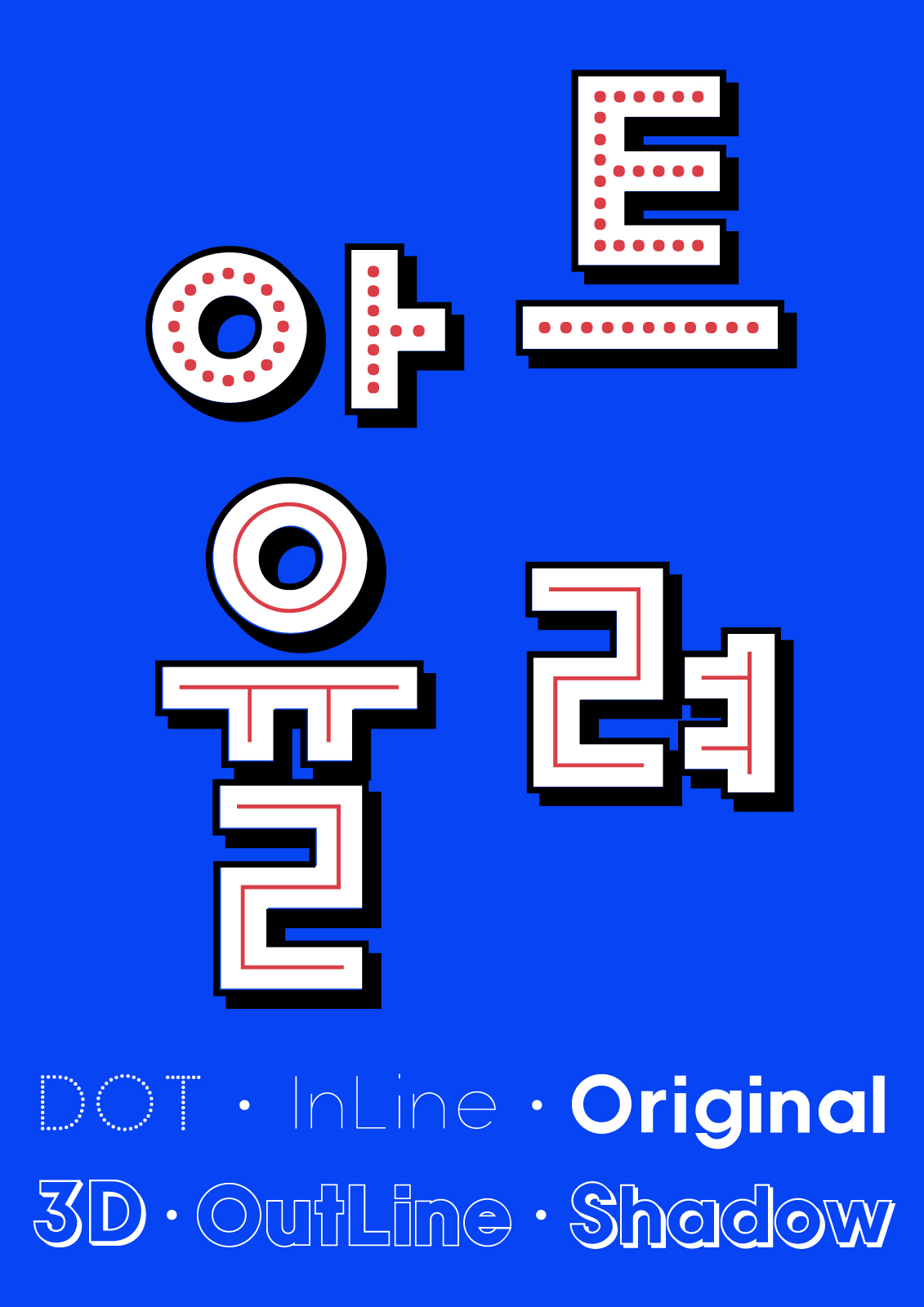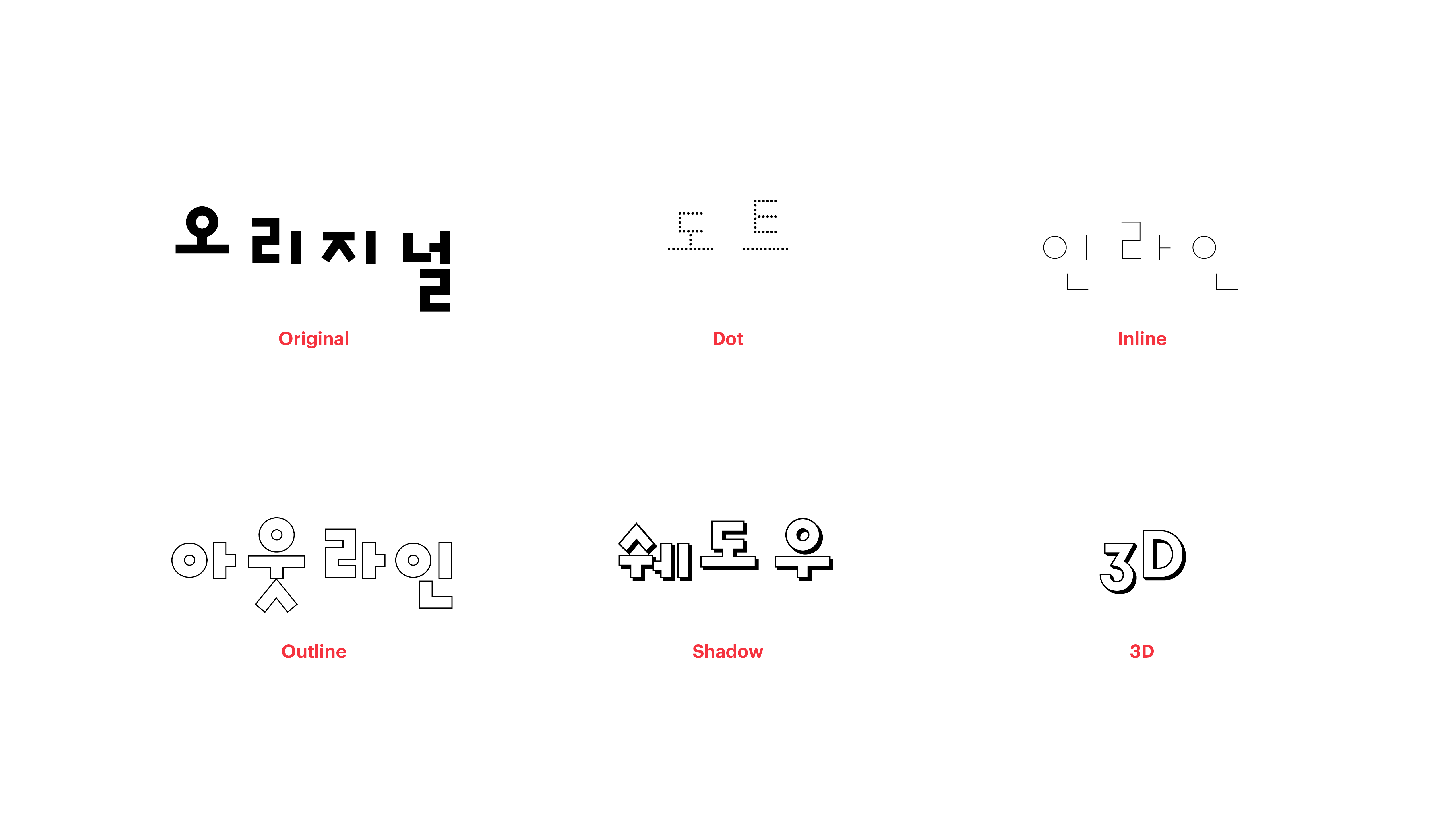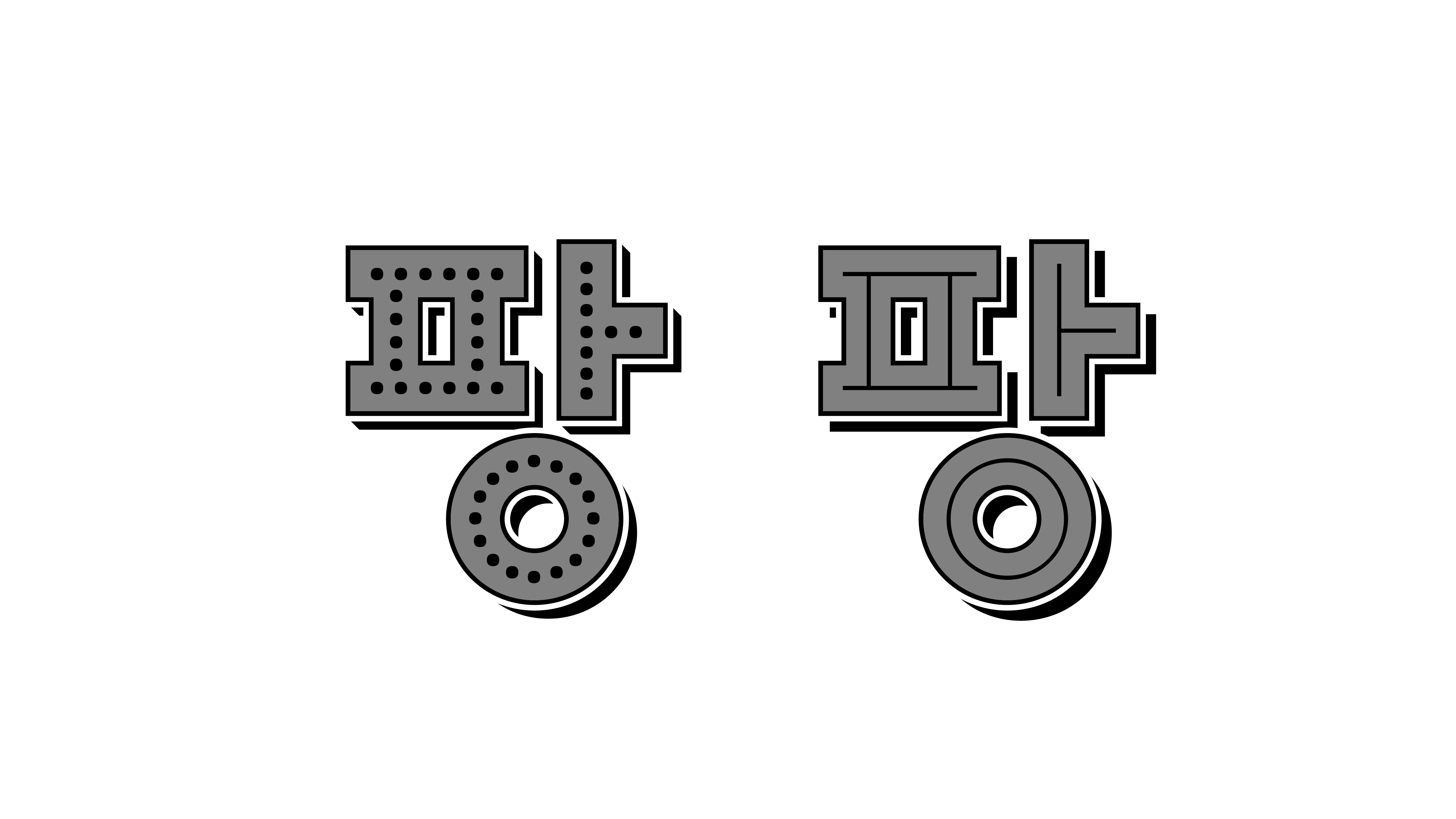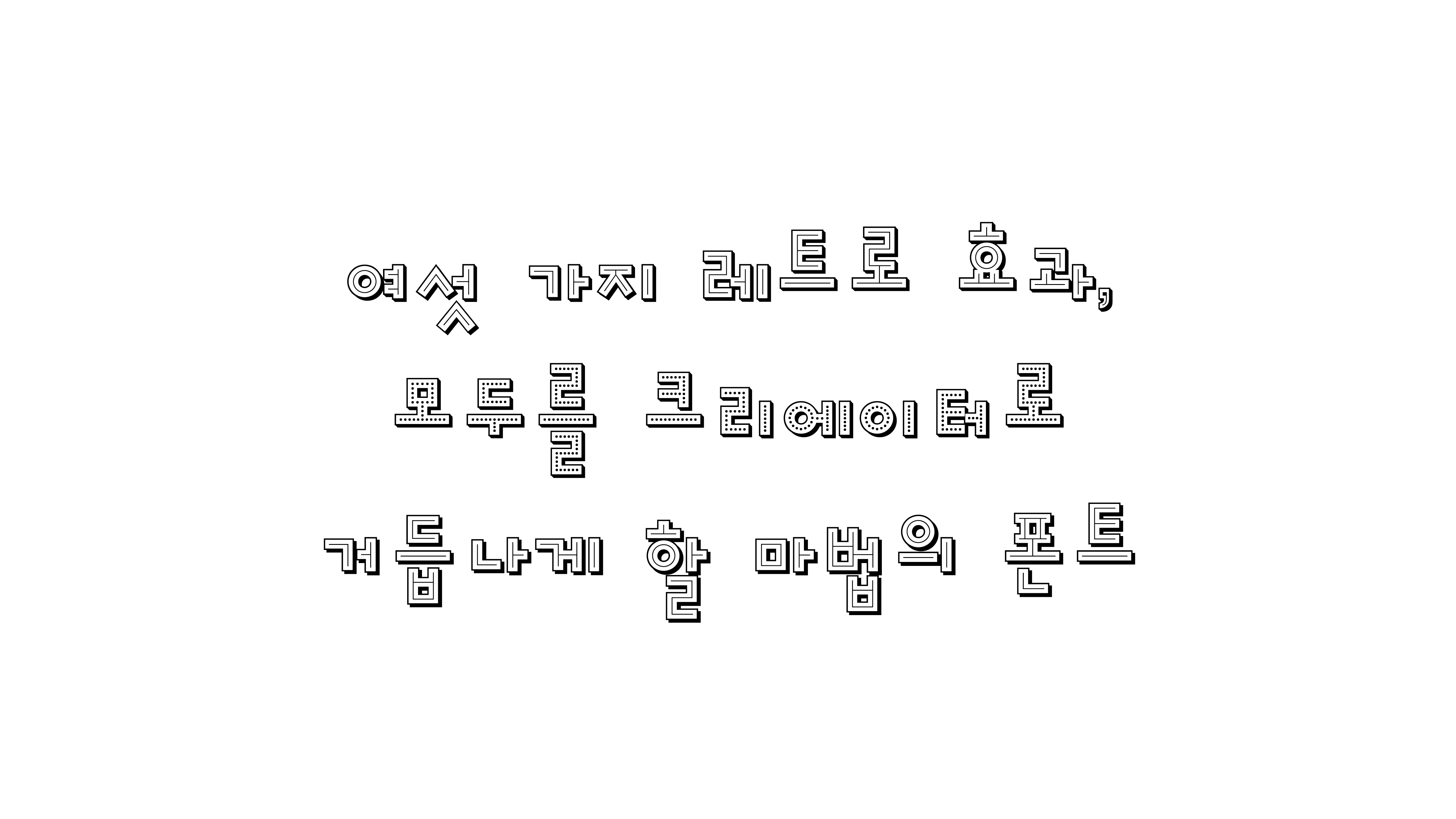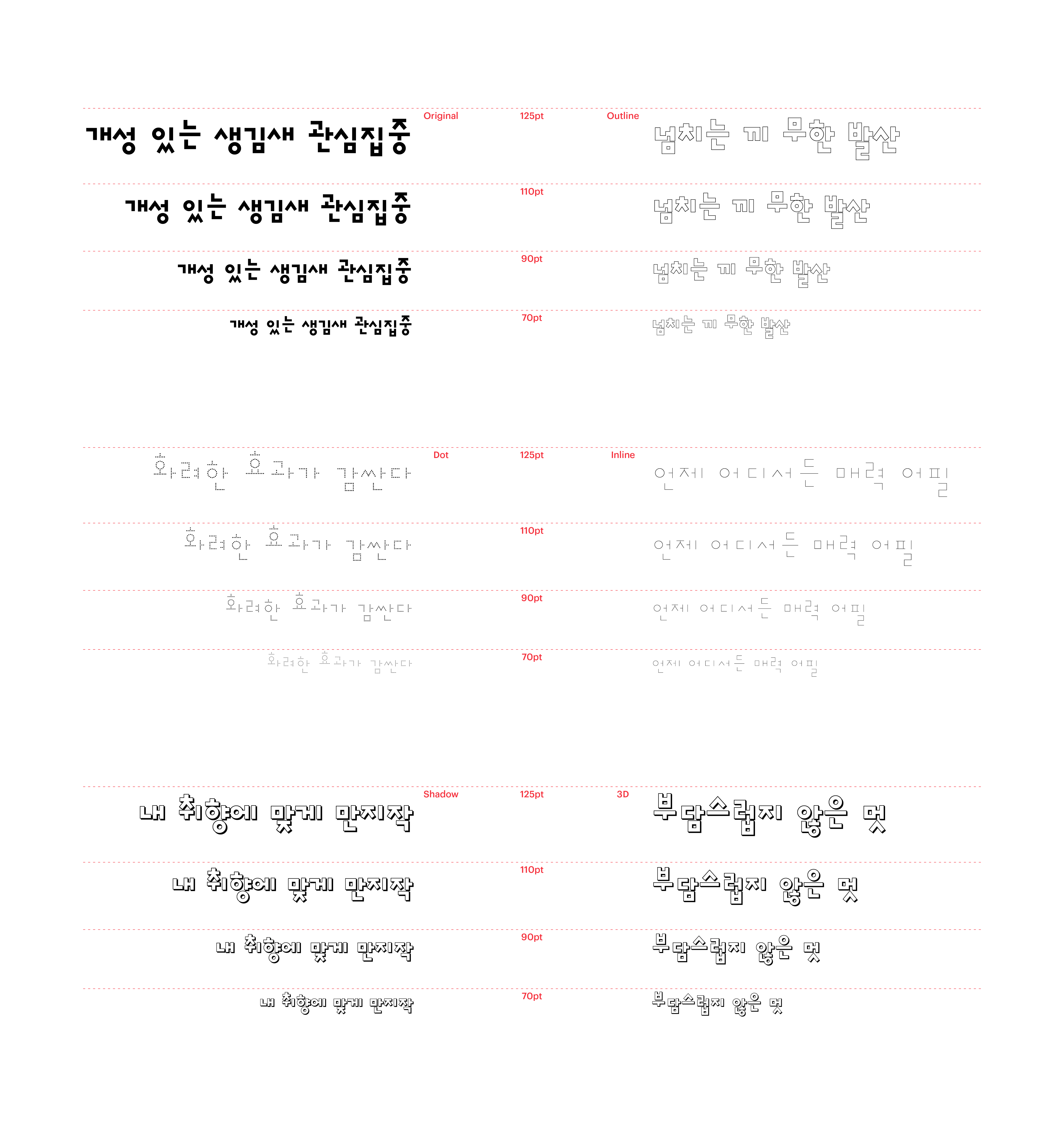
아트율려
Yoon 아트율려
개성 있는 생김새로 커다란 사랑을 받아온 율려체에 오리지널, 도트, 인라인, 아웃라인, 쉐도우, 3D라는 여섯 가지 레트로 효과를 더했습니다. 디자인 툴을 전혀 다룰 줄 몰라도 나만의 개성을 무한 발산할 수 있는 비법, 다름 아닌 바로 폰트에 있다고요!